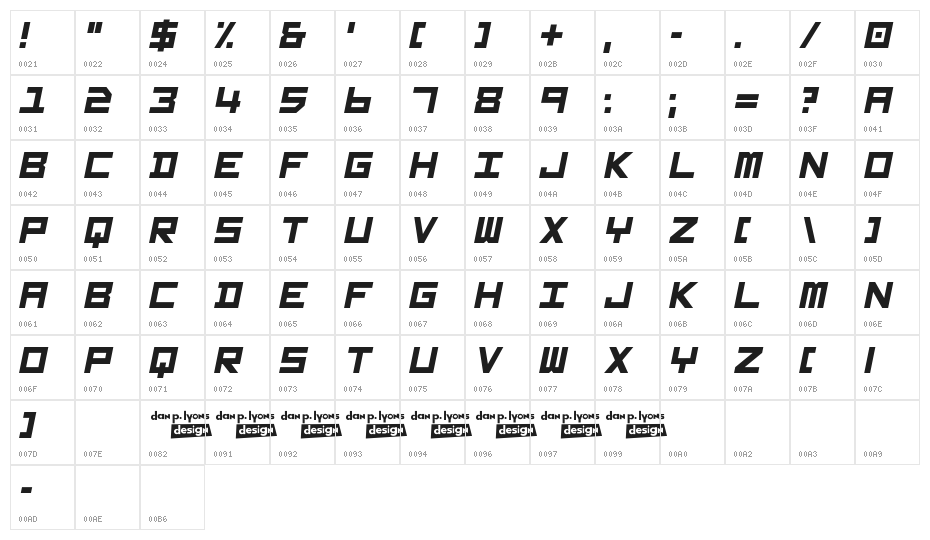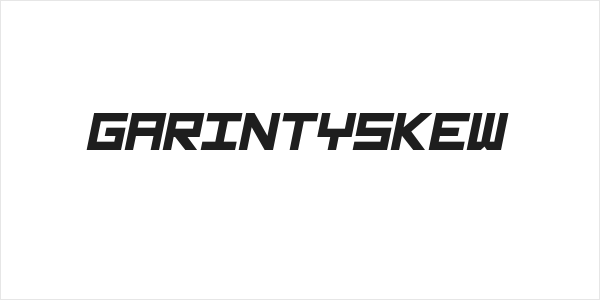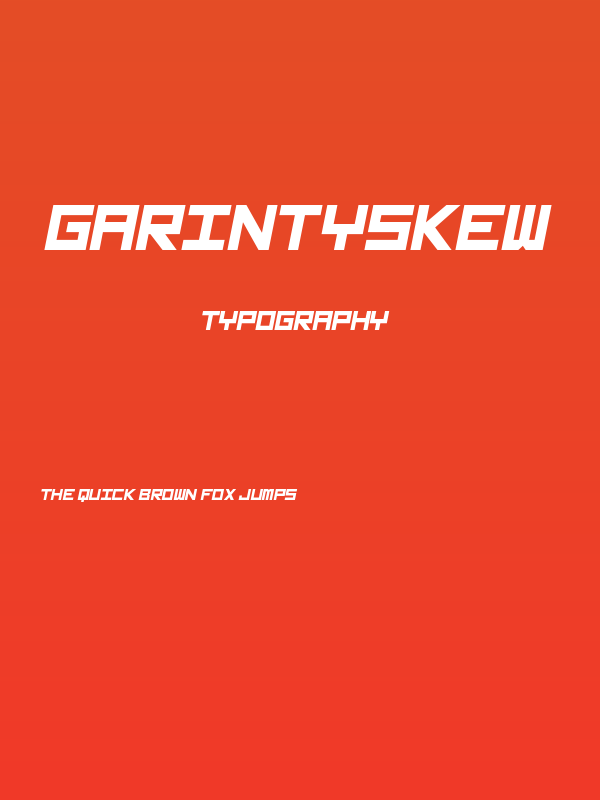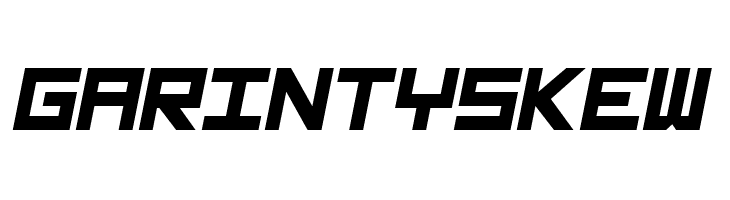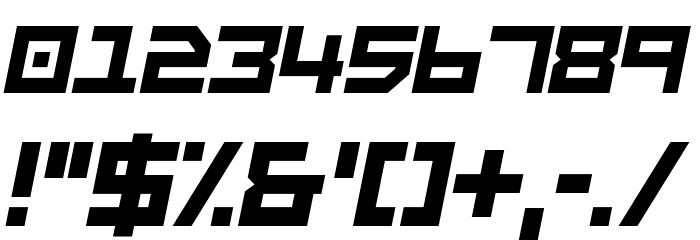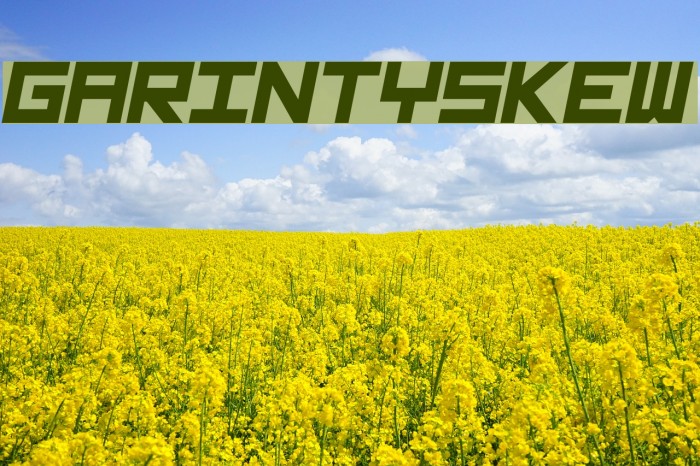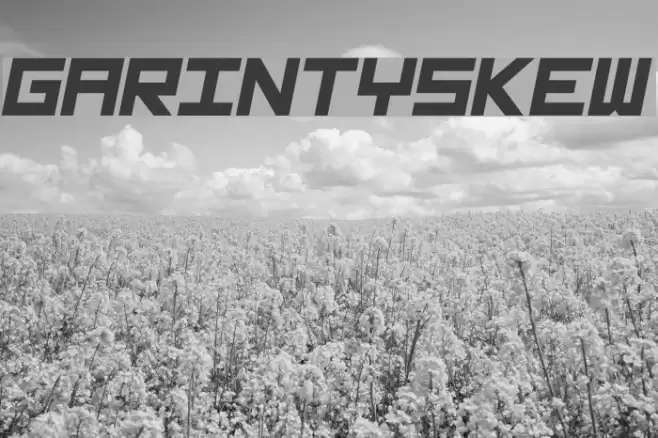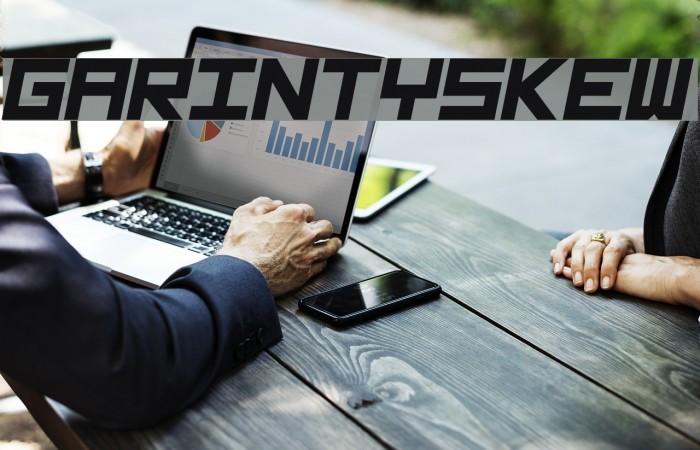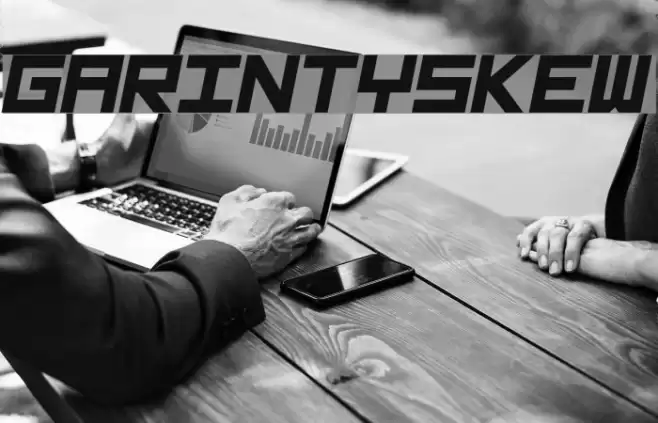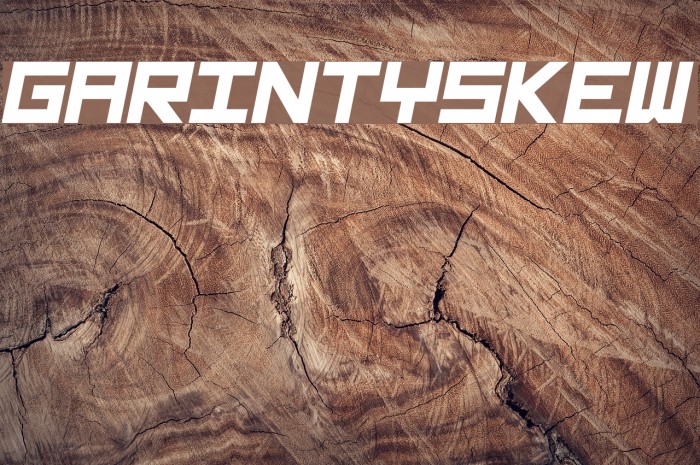
GarintySkew Font
✎ Futuristic
| Vorgeschlagene Projekte | Ideal for technology branding, sports team logos, video game titles, and sci-fi themed designs. |